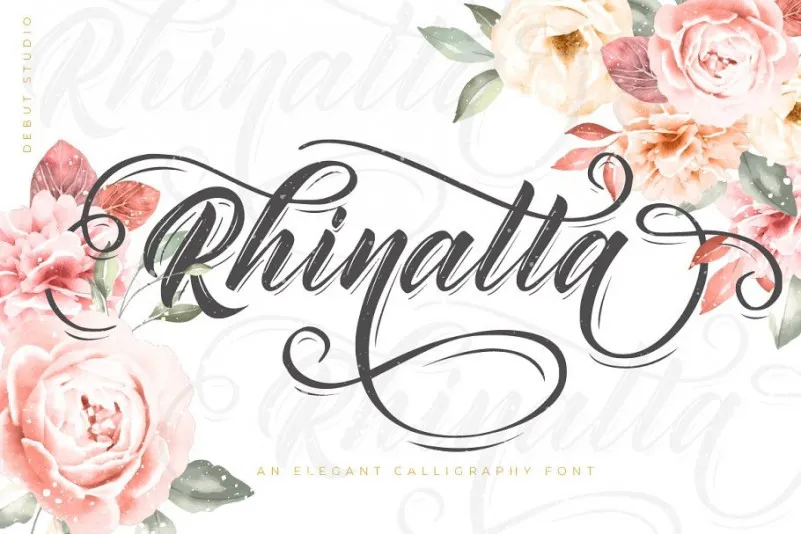
Rhinatta Script Font Demo – Download Grátis
A Rhinatta Script Font é uma opção perfeita para projetistas que buscam um touch elegante moderno. Ela traz à vida designs variados e eventos de forma simples e imediatamente atraente. Esta fonte script moderna, com traços curtos e efêmeros, possui também efeito de destaque e sombra, tornando-a uma escolha ideal para uma variedade de projetos. É perfeita para aplicações no mundo da moda e roupas, como assinaturas, capas de álbuns, logotipos, branding, revistas, mídias sociais e anúncios. A Rhinatta Script Font também se adapta bem a outros tipos de projetos, desde cartazes até designs digitais para sites e aplicativos. Com ela em seu arsenal de ferramentas, seus projetos se tornarão ainda mais criativos e sofisticados. Descubra o estilo único da Rhinatta Script Font agora!